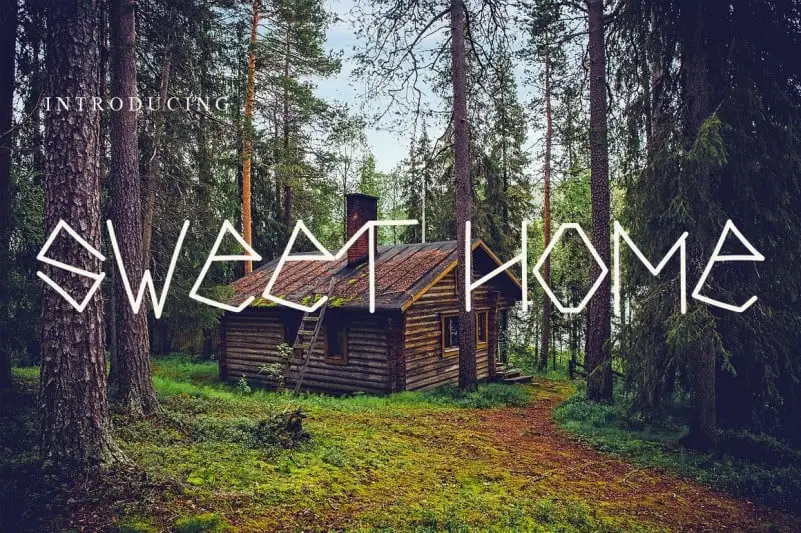
Sweet Home Font – Download Grátis
A Sweet Home Font é uma fonte à mão livre única e incrivelmente quirk que se destaca por sua elegância natural e frescor moderno. Ideal tanto para layouts elaborados quanto simples, ela complementa designs com estilo versátil e permite inúmeras possibilidades criativas. Uma fonte perfeita para quem busca algo diferente e divertido em seu próximo projeto gráfico. Se você está à procura de uma opção original e charmosa, a Sweet Home Font é um ótimo investimento para seus projetos de design. Experimente sua versatilidade e desfrute dos inúmeros ajustes que oferece.